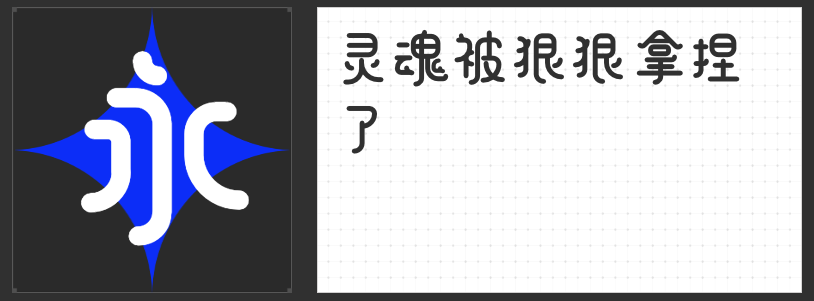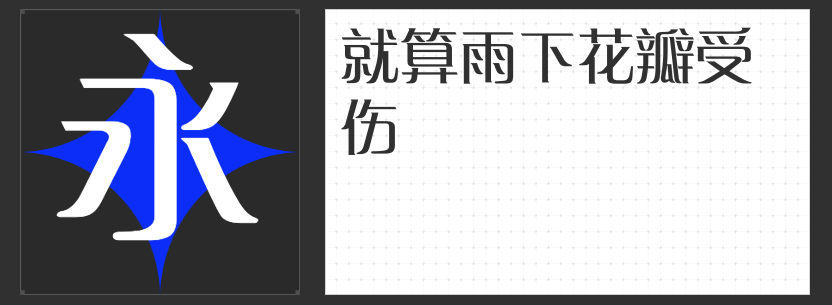
广告设计中的四款“点睛之笔”:解锁创意视觉新维度
在广告设计的视觉语言中,字体不仅是信息传递的载体,更是品牌调性与情感共鸣的催化剂。以下四款非免费字体以独特的设计语言,为广告设计注入鲜活的生命力,成为打破平庸的“秘密武器”。
一、字恋狂漫野 絮风
这款以手写感为基底的直线字体,通过“张弛有度的结构”与“通透的布白空间”构建出动态韵律。笔画设计摒弃传统钩画的尖锐感,转而采用“断开”与“直线组合”的极简手法,使灰度均匀分布,避免视觉疲劳。其字型大小错落的设计,如同音乐中的节奏变化,让版面在统一中暗藏跳跃感,尤其适合需要营造轻松氛围的广告场景,如快消品、短视频封面或文艺活动海报。
二、励字造梦简 特粗
灵感源自“青春筑梦”的这款字体,以“左侧倾斜、右侧竖直”的不对称结构模拟摩天大楼的透视感,棱角分明的直线型笔画传递出强烈的视觉冲击力。设计师通过夸张的透视处理,将文字转化为城市天际线的缩影,赋予广告一种“向上生长”的能量感。适用于科技、运动或房地产类广告,其轮廓清晰的字形在远距离观看时仍能保持辨识度,成为品牌记忆点的核心载体。
三、字恋狂丸粒简
这款字体以“圆角处理”为核心设计语言,笔画两端与转折处的圆润弧度,赋予文字如气球般的轻盈质感。圆头圆尾的笔画形态弱化了攻击性,强化了亲和力,使其成为母婴、食品或宠物类广告的理想选择。其可爱而不幼稚的字型,既能吸引年轻女性群体,又能通过“无害化”设计降低消费者的心理防线,提升广告的信任感。
四、励字励倩简
基于硬笔书写轨迹的这款字体,以“微小圆弧”替代尖锐笔锋,在方正饱满的字型中融入婉转妩媚的气质。笔划粗细对比适中,既保留了手写字体的温度,又通过扁平化设计适配现代审美。其“看似平淡却暗藏韵味”的特性,适合高端美妆、珠宝或文化类广告,以低调的优雅传递品牌格调,避免过度设计带来的俗套感。
广告设计的本质是“用视觉讲故事”,而字体则是故事中的语气与节奏。这四款字体通过结构、笔画与风格的差异化设计,为广告提供了从“力量感”到“亲和力”、从“动态节奏”到“婉约美学”的多元选择。设计师可根据品牌调性精准匹配,让文字成为撬动消费者情感的支点。